Запись времени в рукописном шрифте: как проверить цифры и двоеточие
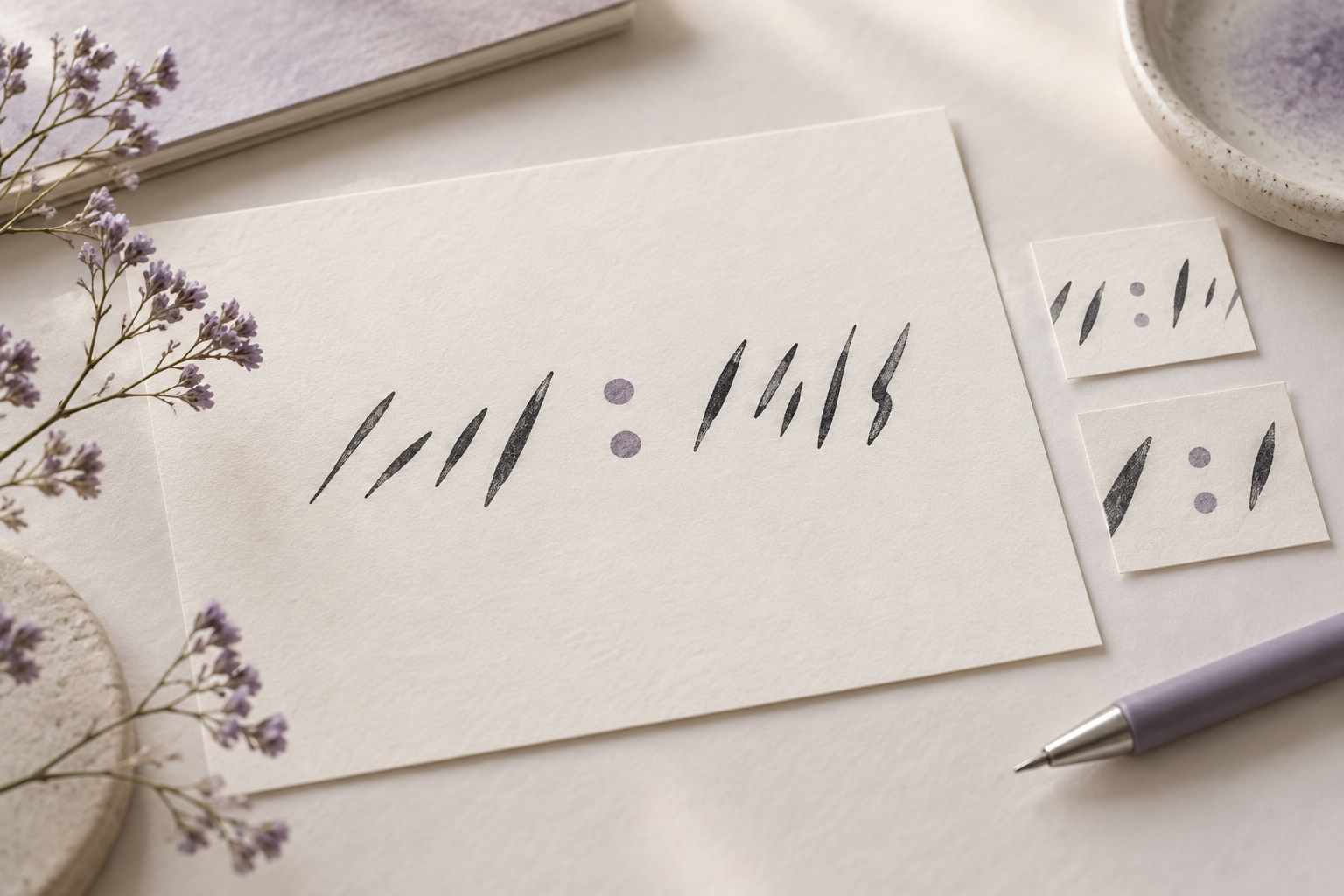
Чтобы время в рукописном шрифте читалось с первого взгляда, проверьте не только отдельные цифры, но и их связку с двоеточием: например, 07:05, 12:30 и 1:09:24. У знака должны быть заметные, но не слишком крупные точки; цифры не должны слипаться с ним или теряться рядом. Ниже — последовательность проб, которая помогает найти проблему до сборки шрифта.
Где встречается запись времени
Часы на расписании, отметка начала занятия, длительность аудиозаписи и время приготовления выглядят похоже, но читаются в разных условиях. В одном макете строку рассматривают внимательно, в другом время нужно заметить краем глаза, пока человек ищет нужный пункт. Поэтому не ограничивайтесь единственным красивым сочетанием вроде 12:34: подготовьте несколько примеров под реальный сценарий.
Время суток часто записывают двумя парами цифр, а длительность может содержать три пары: часы, минуты и секунды. Даже если шрифт в итоге будут использовать только для короткой подписи, проба 00:00 покажет, как повторяются замкнутые формы, а 11:11 — не сливаются ли узкие штрихи в непрерывную гребёнку. Сочетание 08:18 позволяет посмотреть на ноль и петли восьмёрок рядом с разделителем.
Перед рисованием перечислите места, где появятся числа: расписание, табличка с режимом работы, таймер, подпись к видео, карточка рецепта. Уточните, будут ли в строке ведущие нули, секунды, слова «ч» и «мин», а также диапазон времени. Такой список помогает понять, какой именно набор символов требуется проверить, и не превращать проект в абстрактный показательный образец.
Как построить двоеточие для времени
Двоеточие в записи времени выполняет роль зрительного шарнира между группами цифр. Если две точки слишком мелкие, знак может исчезнуть при уменьшении строки или на светлом фоне. Если они чрезмерно крупные и близко поставлены, читатель увидит две отдельные метки, а не единый разделитель. Начните с привычного в почерке круглого или вытянутого штриха и сохраните общую манеру линий, но упростите детали, которые превращаются в шум.
Расположите обе точки так, чтобы вертикальная ось была очевидна. Верхняя и нижняя части не обязаны быть геометрически одинаковыми: рукописный знак может сохранять небольшой наклон или различие в нажиме. Важнее, чтобы в уменьшенном размере точки не сливались в пятно и не распадались на случайную крошку. Посмотрите на знак отдельно, затем вернитесь к строке с цифрами — изолированная форма не показывает, достаточен ли контраст между знаком и соседними штрихами.
Сверьте высоту двоеточия с высотой цифр, а не с произвольной линейкой. Если точки стоят слишком близко к верхнему или нижнему краю цифр, разделитель кажется вытянутым; слишком узкий вертикальный промежуток делает его слабым. В рукописном наборе небольшая асимметрия может выглядеть естественно. Не исправляйте её автоматически до идеальной симметрии: сначала проверьте, остаётся ли знак ясным рядом с разными цифрами.
Важно отличать двоеточие в строке времени от двух точек, случайно поставленных одна над другой. Для проверки распечатайте или покажите несколько контекстов: 07:05, 18:40 и 9:15. Если двоеточие везде выглядит как самостоятельный разделитель, а не часть цифры, значит его положение и поля работают достаточно стабильно. Для длительности добавьте 1:09:24: два разделителя должны восприниматься как повтор одной формы.
Проверьте пары цифр, а не только полный набор
В строке времени важна не только различимость одиночных знаков, но и повторяемость ритма. Пара 11 может стать слишком узкой, 00 — похожей на длинный овал, а 88 — превратиться в плотное тёмное пятно. Проверяйте соседние цифры в сочетаниях, а не делайте вывод по таблице глифов. Для начала достаточно составить короткий набор проб, который включает открытые, замкнутые, узкие и диагональные формы.
Сопоставьте пары и комбинации вроде 00, 08, 11, 17, 20, 22, 55, 68 и 90. Это не универсальный норматив, а удобный набор для наблюдения: в нём встречаются повторения, близкие штрихи, разные ширины и контраст между округлыми и угловатыми рисунками. Добавьте собственные сочетания, если в проекте есть конкретное расписание или важные значения. Не нужно искать ровно такую комбинацию, которая «должна» появиться; задача — увидеть, где формы начинают сливаться.
Сравните 07:05 и 7:5, если формат проекта допускает оба варианта. Ведущий ноль помогает выдержать одинаковую длину часовой пары, но он же добавляет ещё одну форму и может создать тесный участок перед двоеточием. Для карточки расписания с несколькими строками полезно посмотреть и время с нулём, и без него: решение следует принимать по самому макету, а не по эстетическому предпочтению к одной записи.
Обратите внимание на цифры, которые в вашем почерке особенно похожи: например, на 1 и 7, или 3 и 8. Это не повод искусственно сделать каждую цифру непохожей на остальных. Сначала оцените пару на одинаковом размере и в реальном контексте. Удобнее смотреть не только на соседство формы, но и на то, сохраняются ли просветы, направление основных штрихов и общая ширина знака.
Интервалы и ритм строки
Не назначайте механически одинаковую пустоту между всеми символами. Двоеточие уже создаёт видимый разрыв между часами и минутами, поэтому слишком широкие соседние интервалы дробят время на отдельные элементы. Слишком тесная пара, напротив, заставляет две точки прилипнуть к цифрам. Подбирайте боковые поля на контрольной строке и сравнивайте левую группу, знак и правую группу как один ритмический фрагмент.
Поставьте рядом несколько вариантов и меняйте только один параметр за раз: сначала расстояние до двоеточия, затем размер точек, затем ширину цифр. Так легче понять причину улучшения или ухудшения. Если одновременно перерисовать цифру, подвинуть знак и изменить толщину штрихов, результат невозможно оценить без возврата к исходному состоянию. Сохраните исходную пробу или сделайте копию листа, чтобы сравнение оставалось честным.
Проверьте строку в двух масштабах. В крупном виде видны окончание штриха и характер касаний; в малом — только силуэт и интервалы. Для вывески или расписания оцените, читается ли время на той дистанции, с которой его будут искать. Для подписи к ролику посмотрите на сжатый макет, а не только на увеличение в редакторе. Не делайте общих выводов о читаемости всего шрифта по одному самому большому варианту.
Если рядом используются слова, например «начало», «до» или «мин.», добавьте их в пробу. Буквы меняют ощущение расстояния: цифры с узкими формами и слово с плотными строчными могут визуально сблизиться, хотя геометрические поля выглядят одинаково. Поставьте рядом две или три реальные строки расписания и оцените их как систему: разделитель не должен перетягивать внимание сильнее самого времени.
Как собрать контрольную пробу
Для небольшой проверки достаточно подготовить несколько разных строк, а не расписывать всю страницу значениями по порядку. Каждая строка должна проверять конкретное свойство: повторяющиеся цифры, ведущий ноль, различие ширин или запись с секундами. Если вы делаете шаблон для собственного шрифта, включите двоеточие в набор символов и заранее оставьте образцы нужных пар рядом с ним.
Соберите пробу из таких примеров:
- 00:00 и 11:11 — повторы и плотность пар;
- 07:05 и 09:30 — ведущие нули и дважды повторяемый формат;
- 08:18 и 18:40 — округлые формы около разделителя;
- 12:30 и 17:45 — разные силуэты цифр в одной строке;
- 1:09:24 — повтор двоеточия при добавлении секунд;
- две-три реальные подписи из будущего макета.
Этот список — старт, а не универсальный обязательный шаблон. Если для проекта нужны только минуты без секунд, нет смысла искусственно проверять длинную длительность. Если время никогда не начинается с нуля, всё равно полезно увидеть ведущий ноль хотя бы однажды: так вы поймёте, не создаёт ли его форма нежелательный конфликт с ближайшими цифрами.
Сохраните рядом с образцами условия просмотра: размер макета, фон, способ вывода, расстояние или сценарий. Не для отчётности, а чтобы повторить сравнение после правки. Если вы оцифровываете почерк по шаблону Fontgenerator, заполните ячейки цифр и двоеточия в одной визуальной манере, загрузите изображение и проверьте уже извлечённые формы в тех же строках. Так можно заметить, что ошибка возникла при рисовании, съёмке, выравнивании или выделении ячейки.
Частые ошибки при проверке времени
**Смотреть только на двоеточие отдельно.** На крупном увеличении знак может выглядеть аккуратно, а рядом с узкой цифрой 1 стать непропорционально заметным. Возвращайте каждую правку в строку и проверяйте её на соседних формах.
**Оставлять одну пробу с одинаковыми цифрами.** Строка 12:34 не показывает, как работают повторы 00, тонкие пары 11 или открытые контуры 08. Добавьте контрастные сочетания и хотя бы одну строку с нулями в начале.
**Сравнивать только при увеличении.** Деталь, которую удобно рассмотреть на экране, не обязательно сохранится в маленькой подписи. Уменьшите макет до предполагаемого размера и проверьте, остаётся ли разделитель различимым.
**Исправлять разные проблемы одновременно.** Если одновременно передвинуть знак, изменить толщину его точек и перерисовать цифру, вы не поймёте, какой шаг помог. Меняйте один параметр и сохраняйте предыдущий вариант.
**Считать все записи времени одинаковыми.** Строки с секундами, ведущими нулями и текстовой подписью требуют разных проб. Выберите примеры по реальным местам применения, а не добавляйте длинный набор значений без цели.
Чек-лист перед сборкой
- Проверены как минимум повторы 00 и 11.
- В пробе есть время с ведущим нулём и без него, если оба формата нужны проекту.
- Двоеточие заметно, но не конкурирует с цифрами.
- Две точки не сливаются в одну метку при уменьшении.
- Боковые интервалы проверены в строке, а не только в таблице глифов.
- Время с секундами проверено, если такой формат будет использоваться.
- Проба просмотрена в предполагаемом носителе и масштабе.
- После оцифровки формы проверены в тех же контрольных строках.
Нужно ли добавлять ноль перед часом?
Добавляйте ведущий ноль, если он предусмотрен форматом, который использует проект. При разработке формы полезно проверить обе версии — 7:05 и 07:05, — чтобы увидеть влияние дополнительной ширины. Это проверка совместимости с макетом, а не универсальное правило написания времени.
Должны ли точки двоеточия быть строго одинаковыми?
Нет, у рукописного знака допустима небольшая естественная разница. Проверьте, чтобы обе точки воспринимались как одна пара, сохраняли заметный вертикальный ритм и не превращались при уменьшении в кляксу или случайный шум.
Как проверить время с секундами?
Добавьте строку из трёх пар, например 1:09:24, и оцените оба двоеточия вместе. Важно увидеть, повторяется ли рисунок разделителя и остаётся ли строка читаемой целиком, когда групп становится больше.
Можно ли сделать двоеточие крупнее точек в других знаках?
Можно, если в контексте времени оно остаётся частью общей манеры шрифта. Сравните его с обычной точкой, запятой и цифровым набором, а затем проверьте на реальной строке. Не переносите автоматический размер из другой пунктуации без пробы.
Что делать, если время выглядит тесным?
Сначала проверьте, какие именно формы создают тесноту: соседние цифры, боковые поля двоеточия или слишком широкая группа. Измените один параметр, сравните несколько строк и выберите решение, которое работает не только для единственного времени.
Когда повторять проверку после правок?
Повторяйте её после изменения двоеточия, ширины цифр, масштаба шаблона или способа оцифровки. Контрольная строка быстро показывает, затронула ли локальная правка соседние сочетания, даже если сами одиночные символы выглядят неизменными.